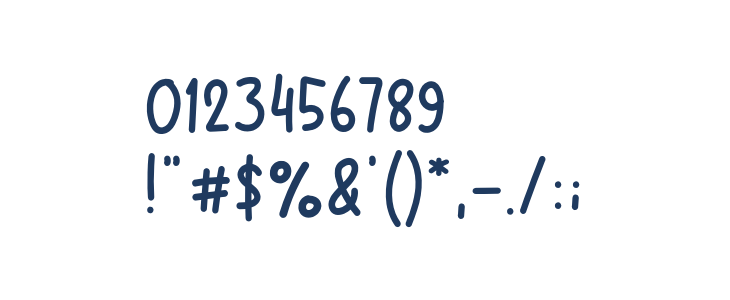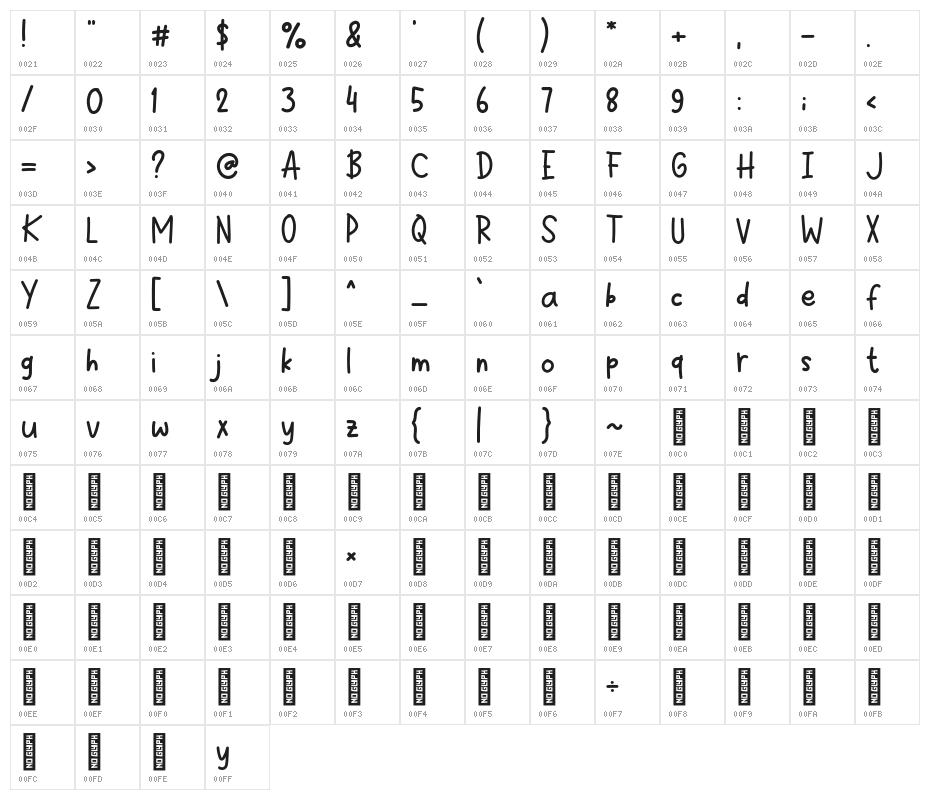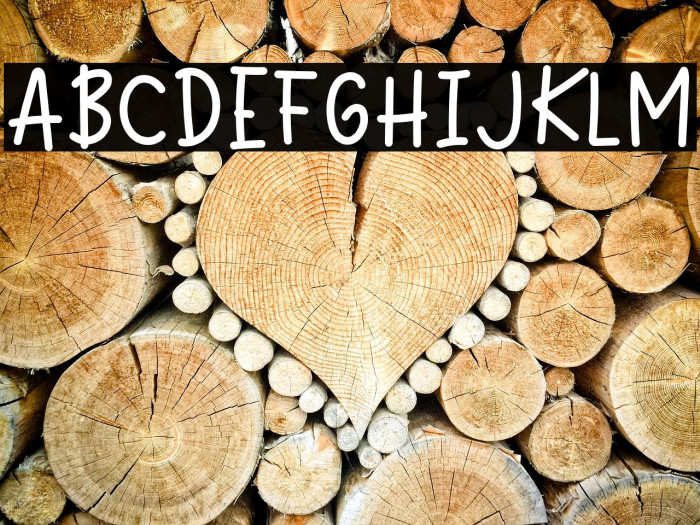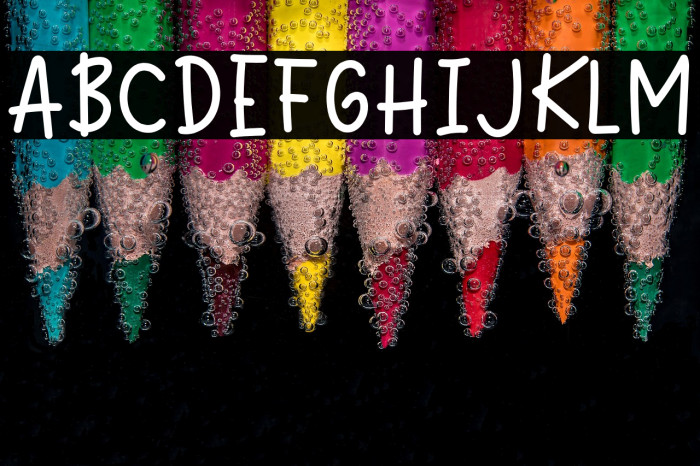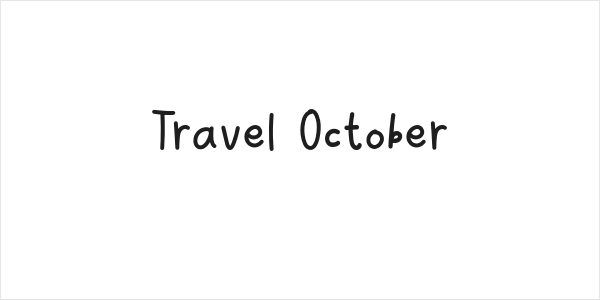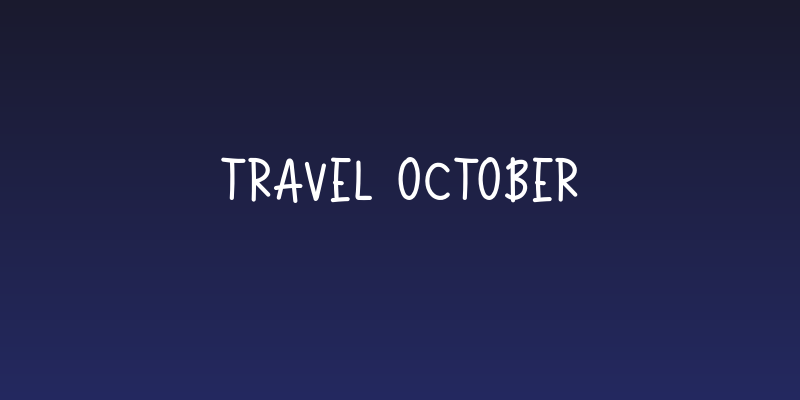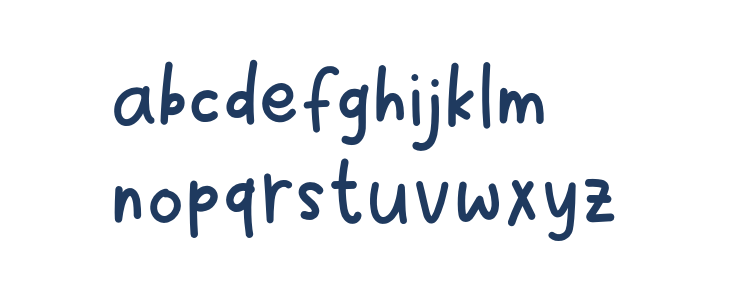
Travel October Font
| Gesamtstil | Casual |
| Anwendungsfall | Headlines, Informal text, Creative projects |
| Vorgeschlagene Projekte | Ideal for greeting cards, children's books, casual branding, and social media graphics. |